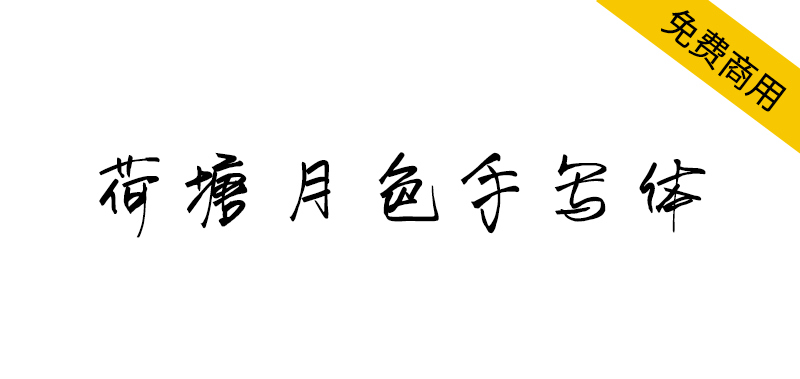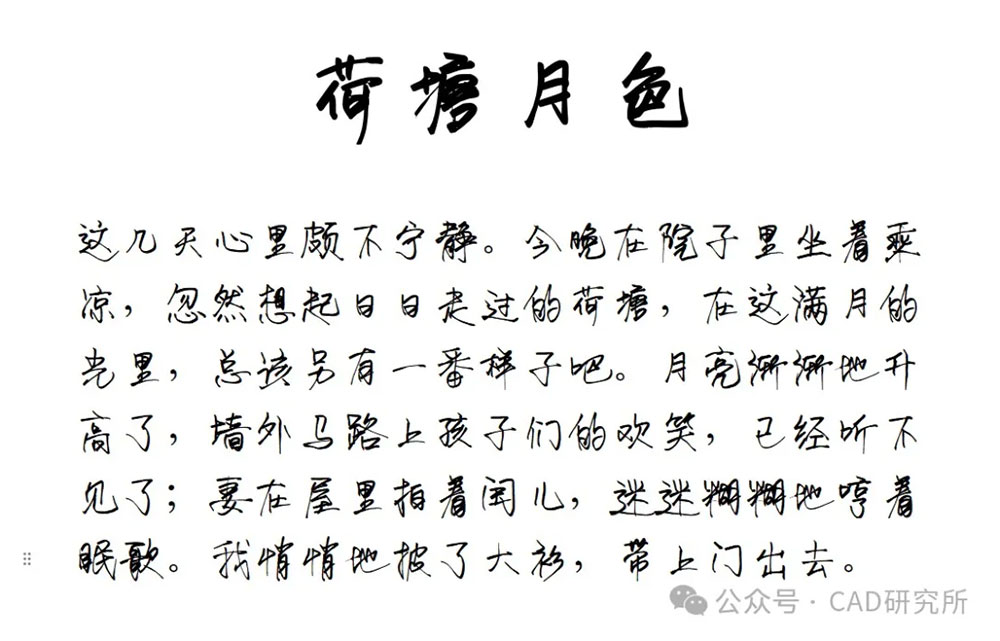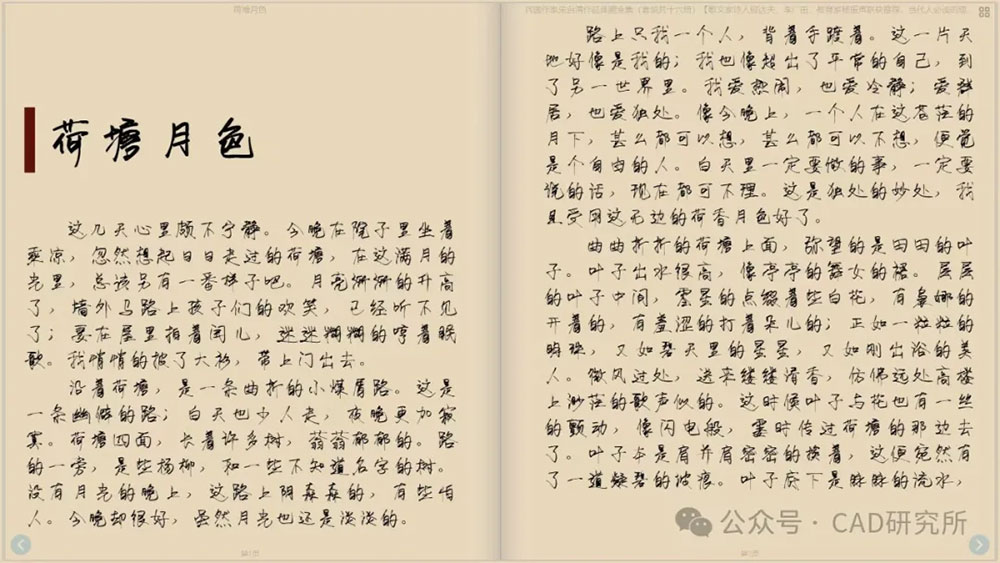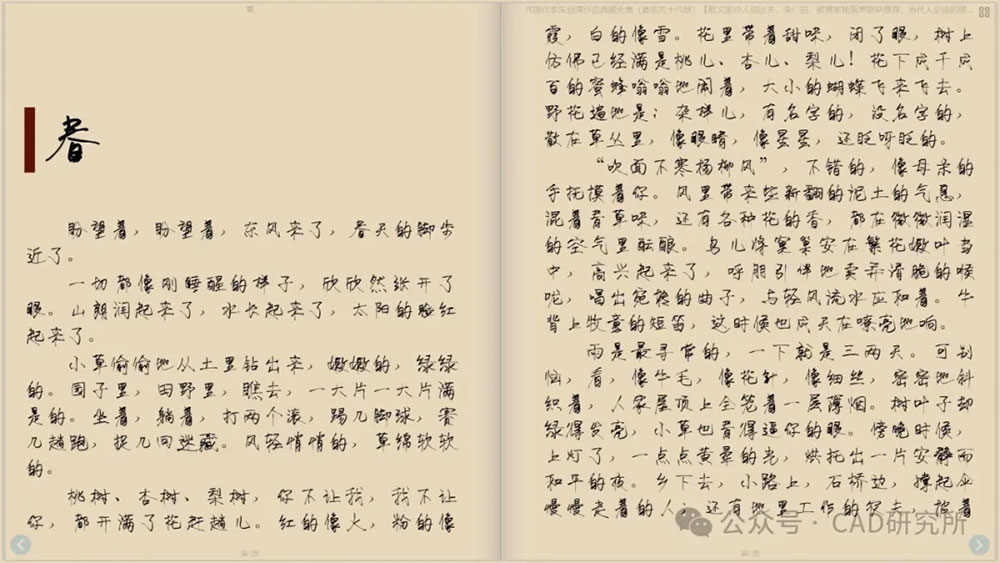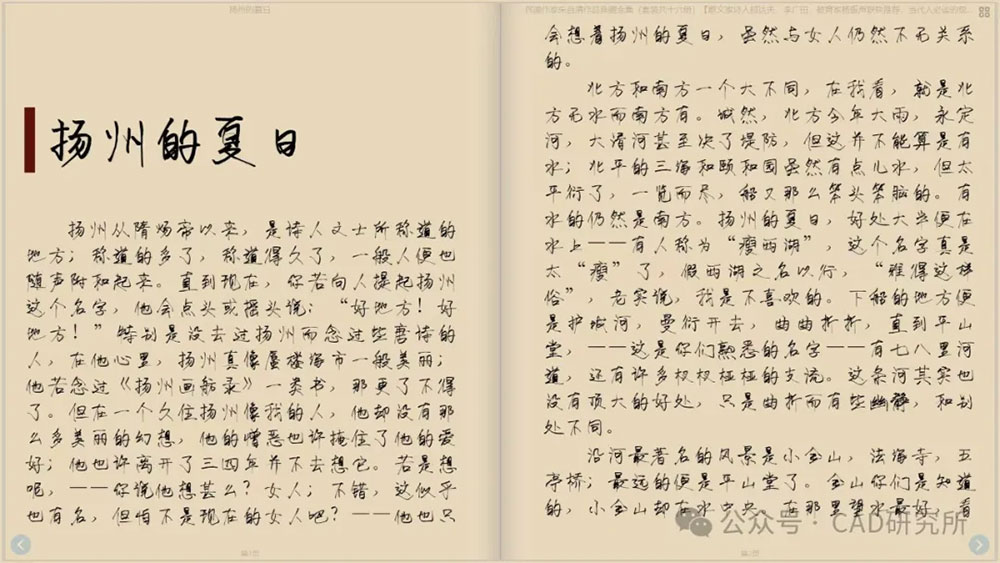
创作动机:作为一名深化设计师,我在工作中常常需要手绘线条,同时手写文字以辅助表达。然而,有时候文字较多,逐个书写不仅麻烦,也可能影响美观。因此,我决定设计一款手写字体,以后便能一劳永逸,免去手写的烦恼。
名称由来:最初,我为这款字体取名“豆角豆角手写体”,因为我的女儿小名叫“豆角”。这也算是送给她的一份礼物。当她长大后,能够使用这款字体时,她所打的每一段话,仿佛都是爸爸亲手写给她的,相信她一定会喜欢。
写字其实有些枯燥,所以在创作初期,我并不是按照字典从头到尾开始写,而是挑选一些我喜欢的文章来进行书写,顺便测试排版效果。其中,有一篇恰好是朱自清的《荷塘月色》。开篇的第一句话:“这几天心里颇不宁静”,深深触动了我。作为一个设计师,反复修改作品确实让人心情不宁静。读到朱自清悄悄披上大衫走出门外的情景时,我想,1927年的朱自清或许也是个白天上班后感到疲惫,晚上外出散心的人吧。与文中那种既有淡淡的喜悦,又有淡淡的哀愁的复杂情感,我不禁感同身受。作为同为父亲的人,我倍感共鸣。
文字流淌了百年,但依然为无数人带来心灵的慰藉。于是,我决定将这款字体命名为“荷塘月色”,因为我开始创作这款字体时,正是在一个盛夏的夜晚。希望大家在使用这款字体时,能感受到它名称所蕴含的意境,体会到内心的宁静。